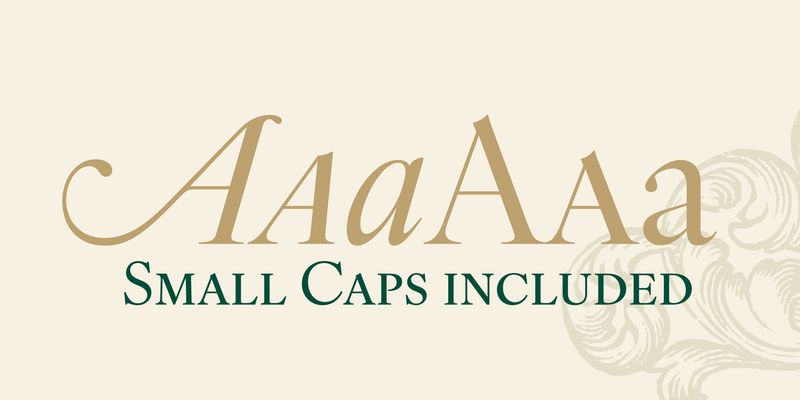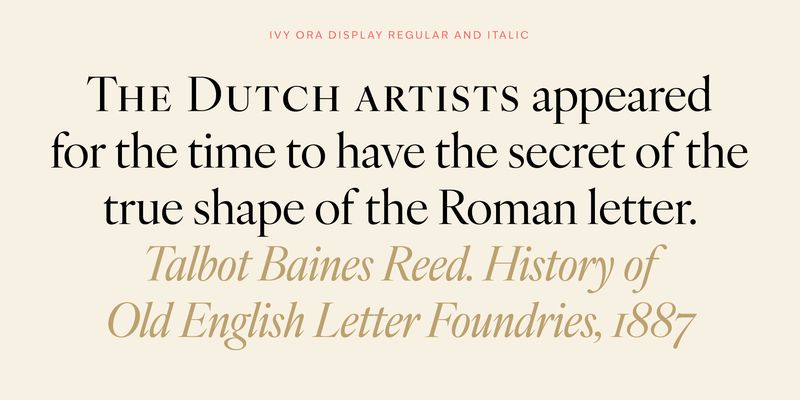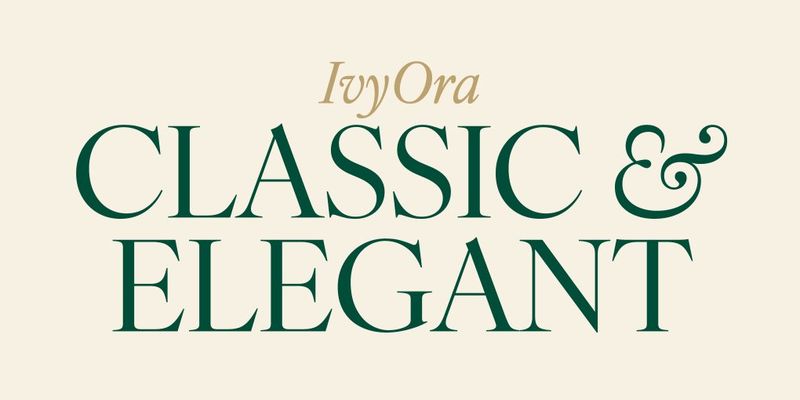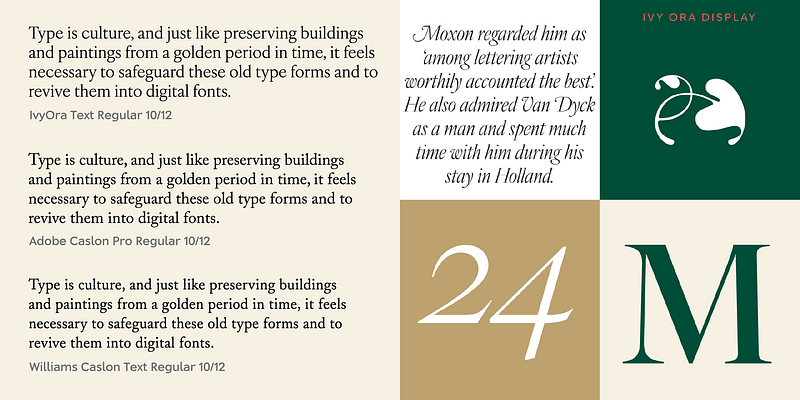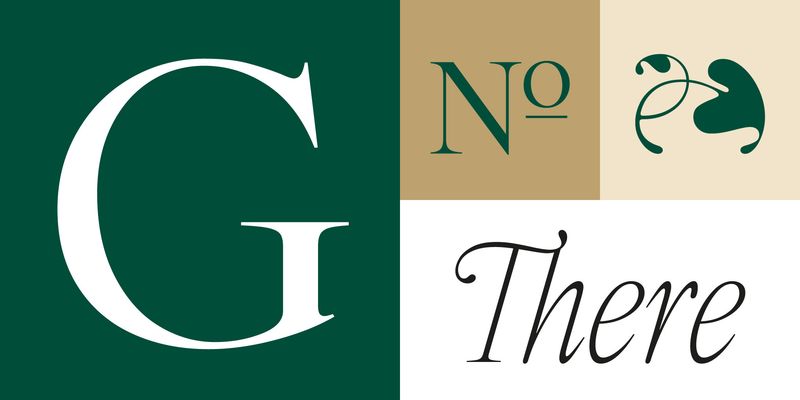
IvyOra は、アントワープのプランタンモレトゥス博物館で発見された歴史的な標本から作成されたオランダのオールドフェイスのリバイバルです。大部分は、1695 年に発行された Dirck Voskens のウィドーの Proef van Letteren と呼ばれるフォリオシートからのものです。イタリック体の標本は、Christoffel van Dijck (彼の時代には、オランダで最も偉大なオールドフェイスタイプのパンチカッターとして知られていた) によるものである可能性があります。
Ivy Foundry はデンマークを拠点とする独立経営の小規模な活字鋳造所です。2016 年に Jan Maack 氏によって設立されました。その社名は、句読点や植字上の装飾として使用される絵文字、フラーロンに由来します。フラーロンは最も古くから存在する植字上の装飾の 1 つで、古代ギリシャやローマの碑文にも使われています。フラーロン (ラテン語ではヘデラ) は、蔦の形がモチーフとなっています。